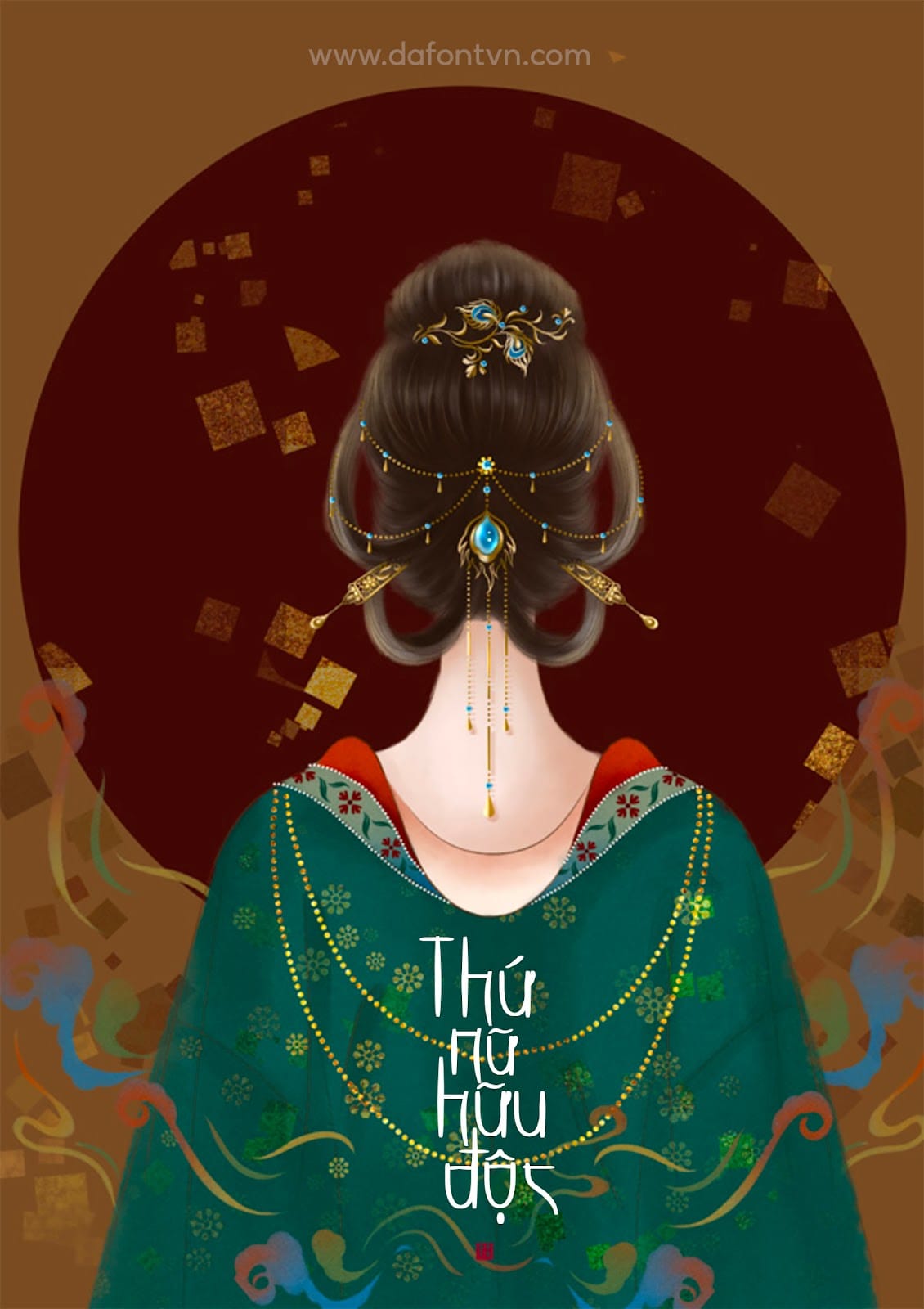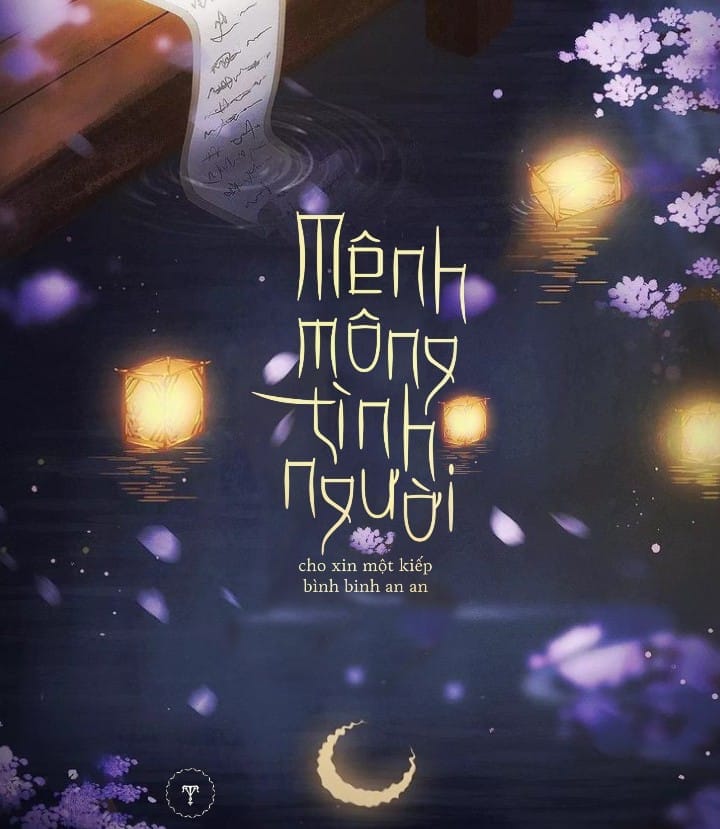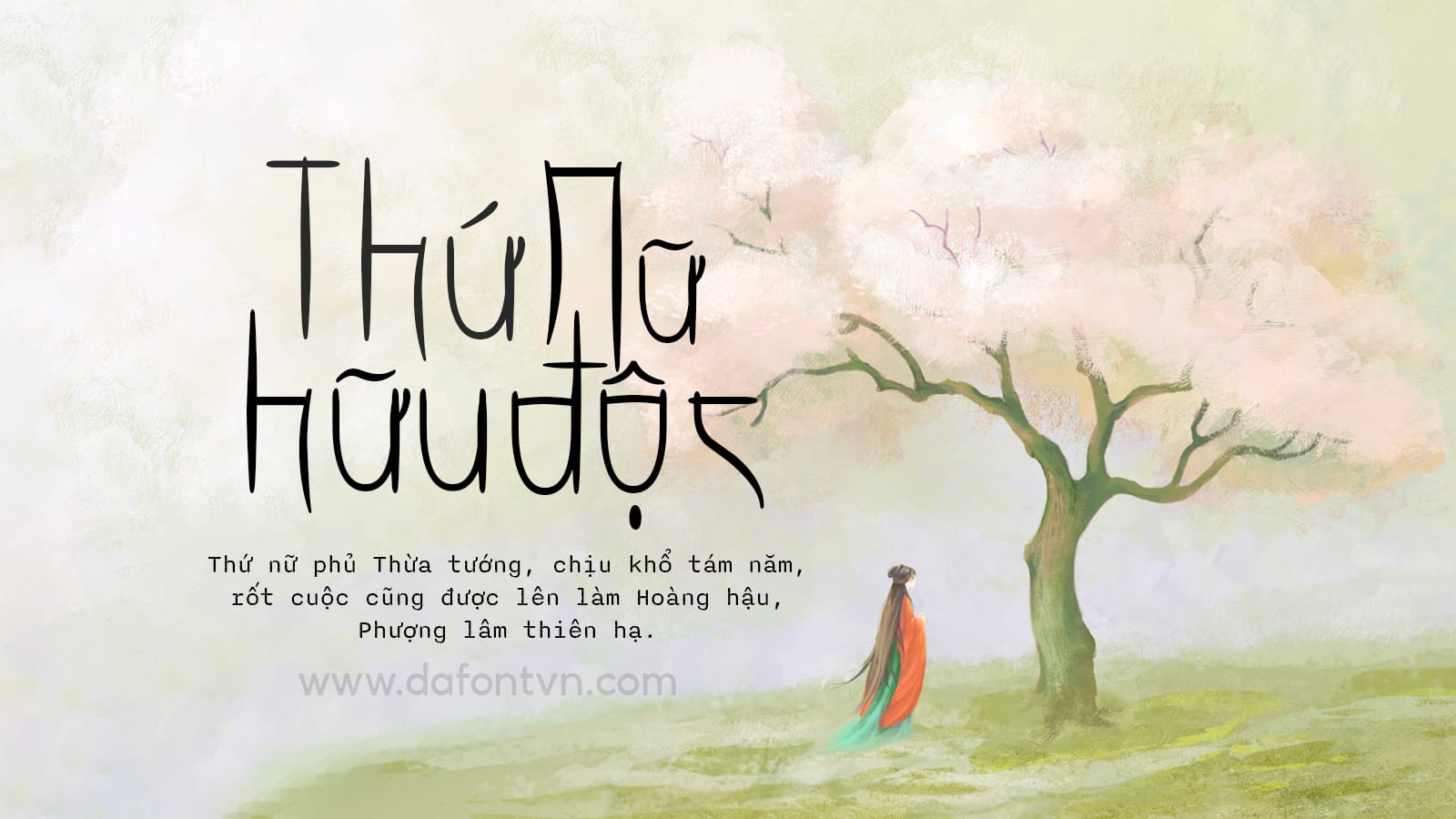
Giới thiệu đến các bạn một font cổ trang việt hóa TLM Take cực đẹp phù hợp với các thiết kế cổ trang, bìa sách, bìa truyện, thiệp mời… hay bất kỳ thiết kế nào khác. Font chữ với ký tự thường và ký tự in hoa do đó bạn có thể kết hợp để tạo ra tác phẩm tuyệt vời cho riêng mình. Font được thiết kế lấy cảm hứng từ chữ viết tay với các nét và dấu mang phong cách Trung Hoa.